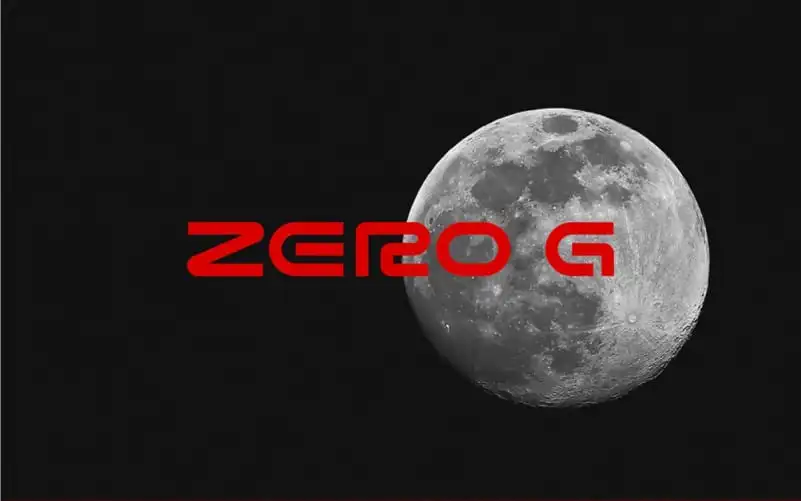
A Zero G Display Font é uma nova opção para designers de logotipos minimalistas. Este tipo digital foi criado por Aromal Ashok com inspiração na tecnologia espacial e futurismo. Perfeito para criações gráficas como cartazes, roupas, headlines e logos, a Zero G Display é ideal para quem busca uma fonte que moderniza o design ao extremo. Seu uso permite destacar letras individuais através da alternância de caracteres. Para quem quer imprimir grandes textos em alta resolução ou projetar materiais publicitários em grande escala, esta é uma ótima opção. A Zero G Display Font pode ser usada não apenas para criar logotipos e marcas corporativas minimalistas, mas também para tags de produto, headlines de sites ou até mesmo camisetas. Suas linhas finas e formas geométricas tornam-na perfeita para aplicar em qualquer meio digital ou impresso, criando um design que se destaca do resto da concorrência. Seja através dos seus logotipos ou marcas digitais, ou nos posters de sua marca impressa, a Zero G Display Font promete deixá-la surpreso com seu desempenho e versatilidade.